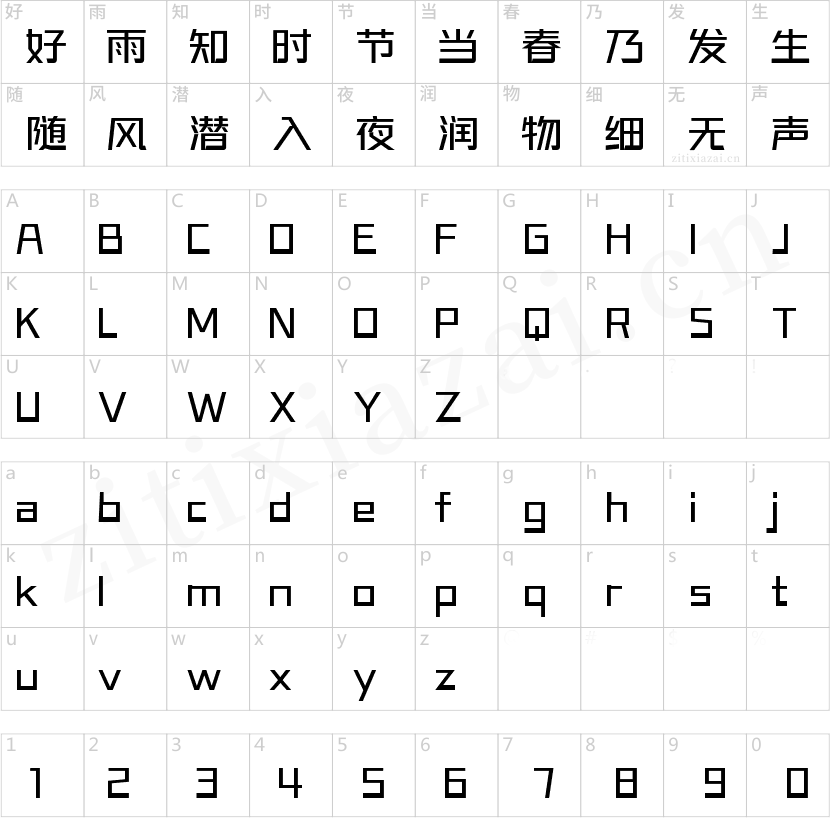
字魂源力觉醒黑
字魂字体字魂源力觉醒黑字体是由字魂创意字库设计并生产的一款可商用的字体,被收录于字魂先锋系列。该字体支持GB-2312标准以及最新的字魂ZH7144标准,包含7144个中文、字母、符号和数字,字体类型偏向黑体,具有力量、时尚、帅气的风格,在市面上广泛用于荣誉证书、企业文化、党政公务等场景。